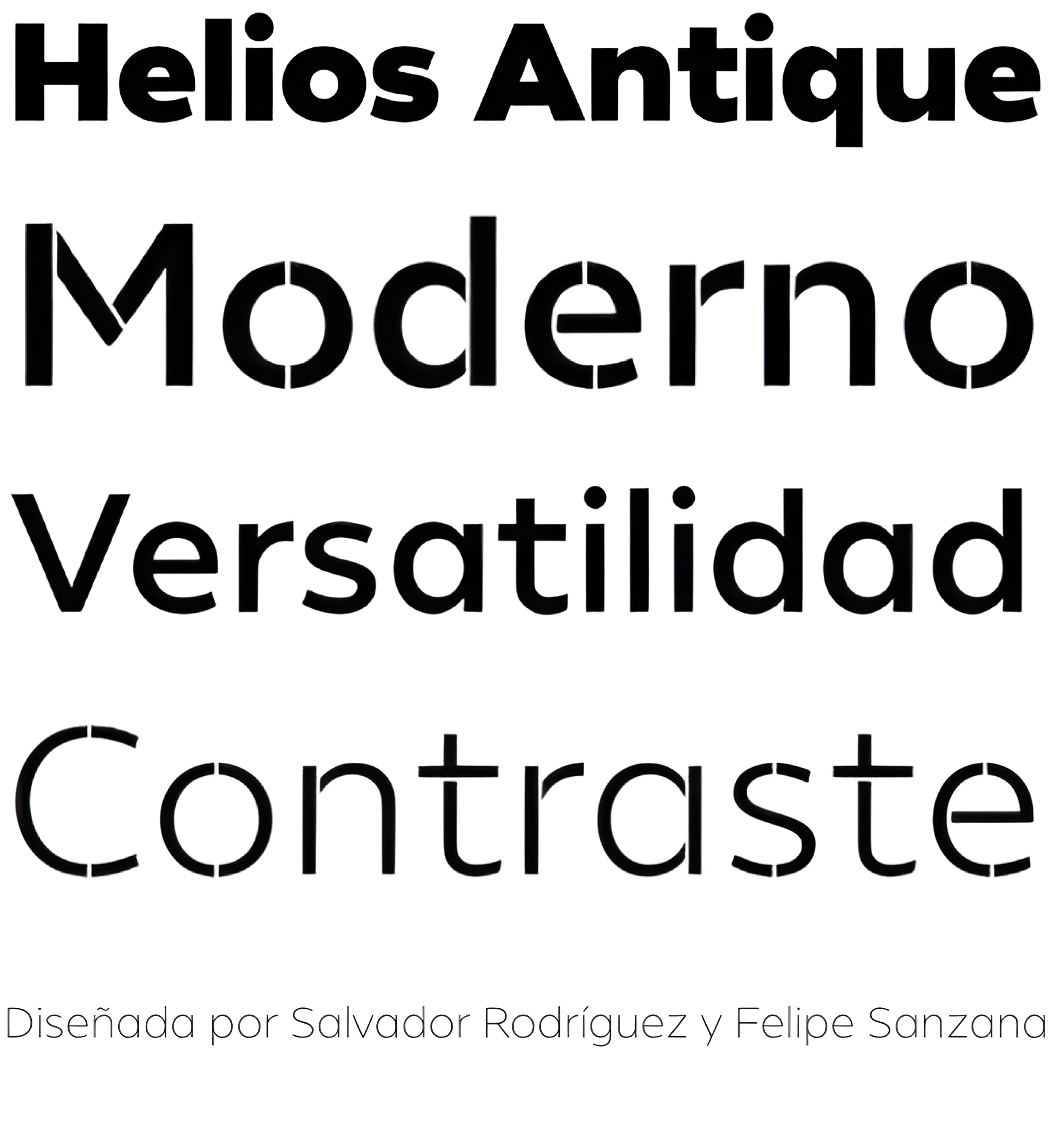
| Descripción | La familia tipográfica Helios es el resultado de una mezcla entre las primeras sans serif y las tendencias modernas de nuestra época. Su estructura racional es sutilmente más ancha que la mayoría de las primeras sans, generando un mayor impacto en sus usos. Todos los terminales tipográficos son más abiertos para equilibrar mejor los blancos y negros de Helios, y donde se juntan los trazos tiene un contraste más profundo que da más legibilidad al lector. Además, en algunas letras es posible ver algunos rasgos prominentes, como la pierna de la «R»; y la cola de la «Q», que son gestos particulares que identifican a esta familia tipográfica. Helios Stencil es la versión resistente de esta familia tipográfica. Todos los huecos del stencil se midieron rigurosamente, por lo que en tamaños pequeños transmite una estética neutra, mientras que en tamaños grandes aparece una lógica de visualización. Helios Antique se compone de 36 estilos, 782 glifos y versalitas. Además, cuenta con potentes características OpenType para cada estilo, como caracteres alternativos, ligaduras, fracciones, números especiales, flechas, soporte ampliado de idiomas y muchas más. |
| Familia(s) | Helios Antique |